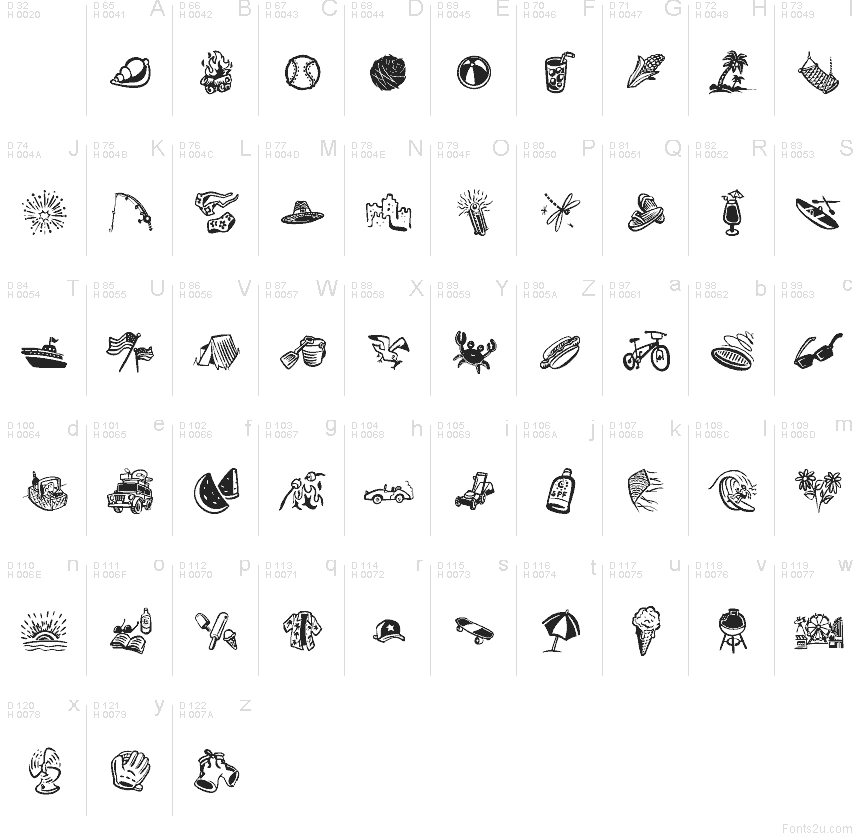
Summer88
2025年にリリースされたBen Dunkleの無料サマー・ディングバット・フォント「Summer 88」は、夏の爽やかなアイコンを遊び心あふれるコレクションに詰め込みました。太い黒の輪郭線、少し揺らぎのある手描きの曲線、そして花、アイスクリーム、サーフボード、荷物満載のビーチトラックといった親しみやすいバケーションのモチーフが、大胆でカートゥーンのような雰囲気を醸し出しています。
ポスター、パーティーの招待状、季節のグッズ、スクラップブック、キャンプのグラフィック、SNS投稿など、ちょっとしたグラフィックが文字以上に語りかけるような場面に自然と馴染みます。無料のフォントとして、タイトルカードやバッジ風のレイアウト、素早いブランディングのアクセントにも最適です。シンプルで明るいシンボルは、カジュアルなレタリングと非常に相性が良いのが特徴です。
Ben Dunkle, 2025
A smattering of fun, retro summer icons